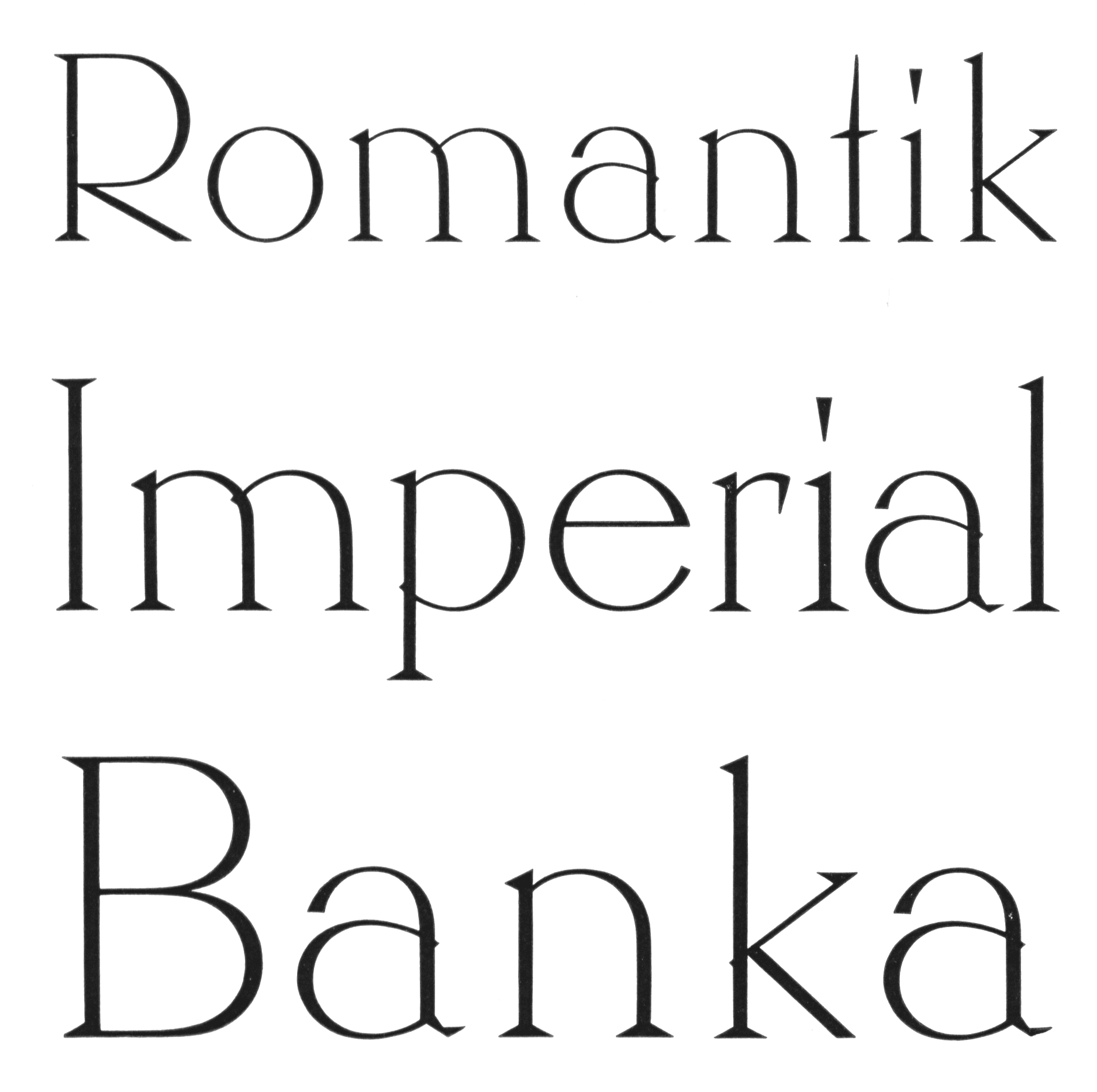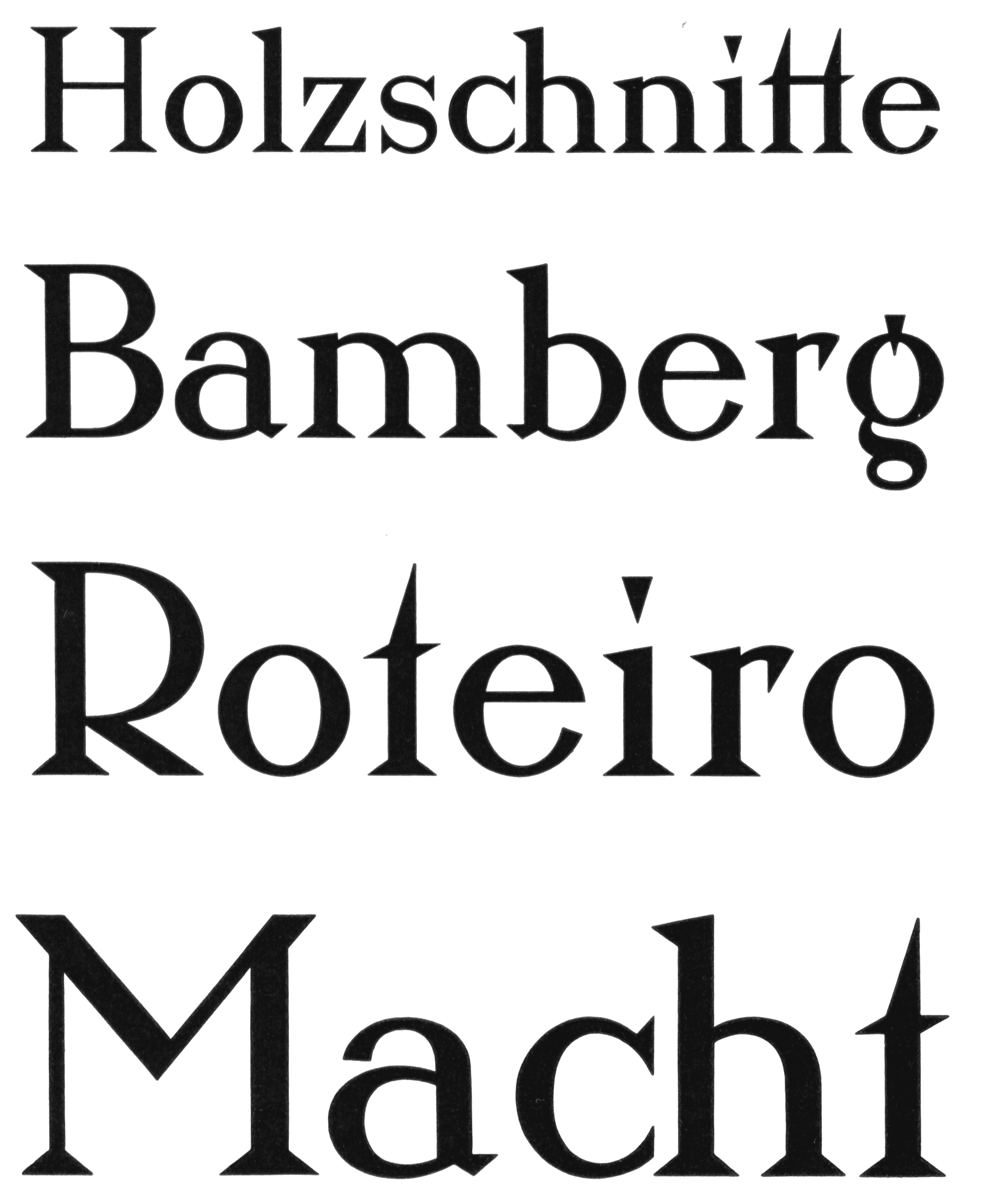
Font-Wiki: Klinger-Type
Die Klinger-Type ist eine konstruierte Antiqua mit Dreiecksserifen. Der magere Schnitt erschien 1925 bei der Schriftguß in Dresden. 1927 wurde ein kursiver und ein halbfetter Schnitt nachgelegt. Der offizielle Urheberverweis lautete »nach Zeichnungen der Klinger-Gruppe Wien«.
Digitalisierungen sind nicht bekannt.